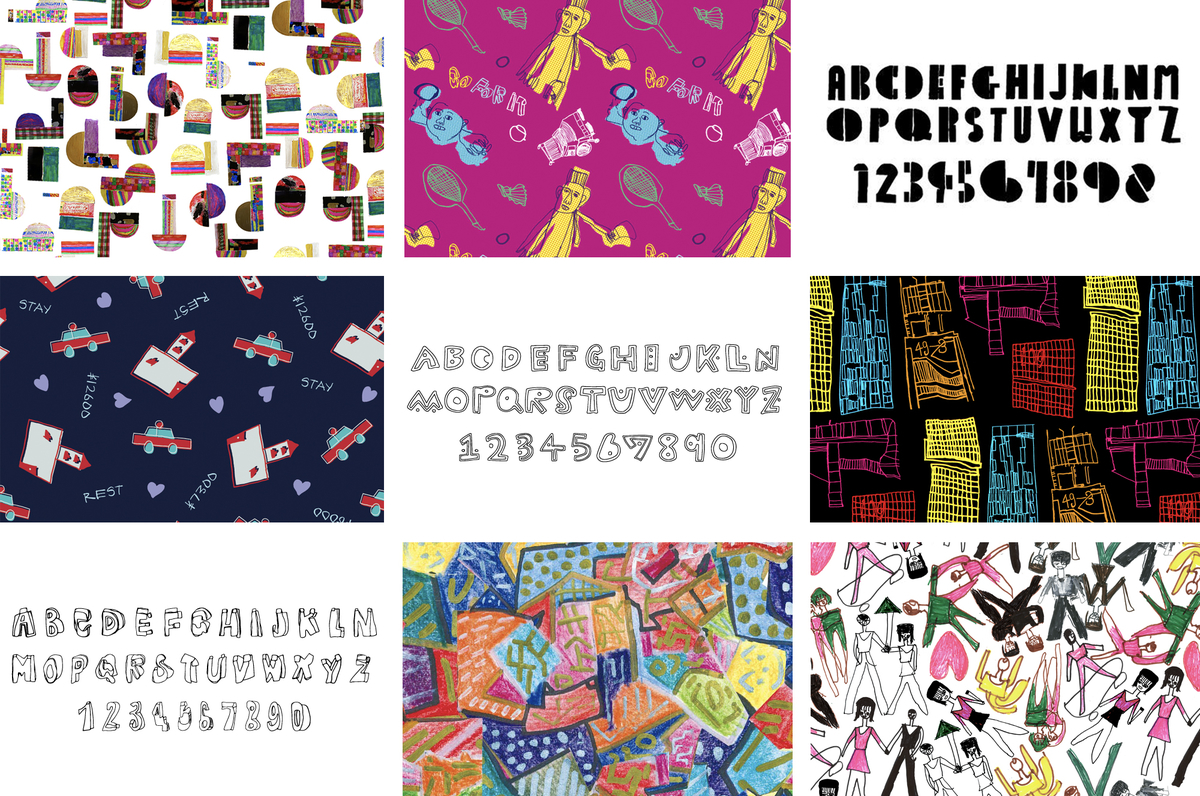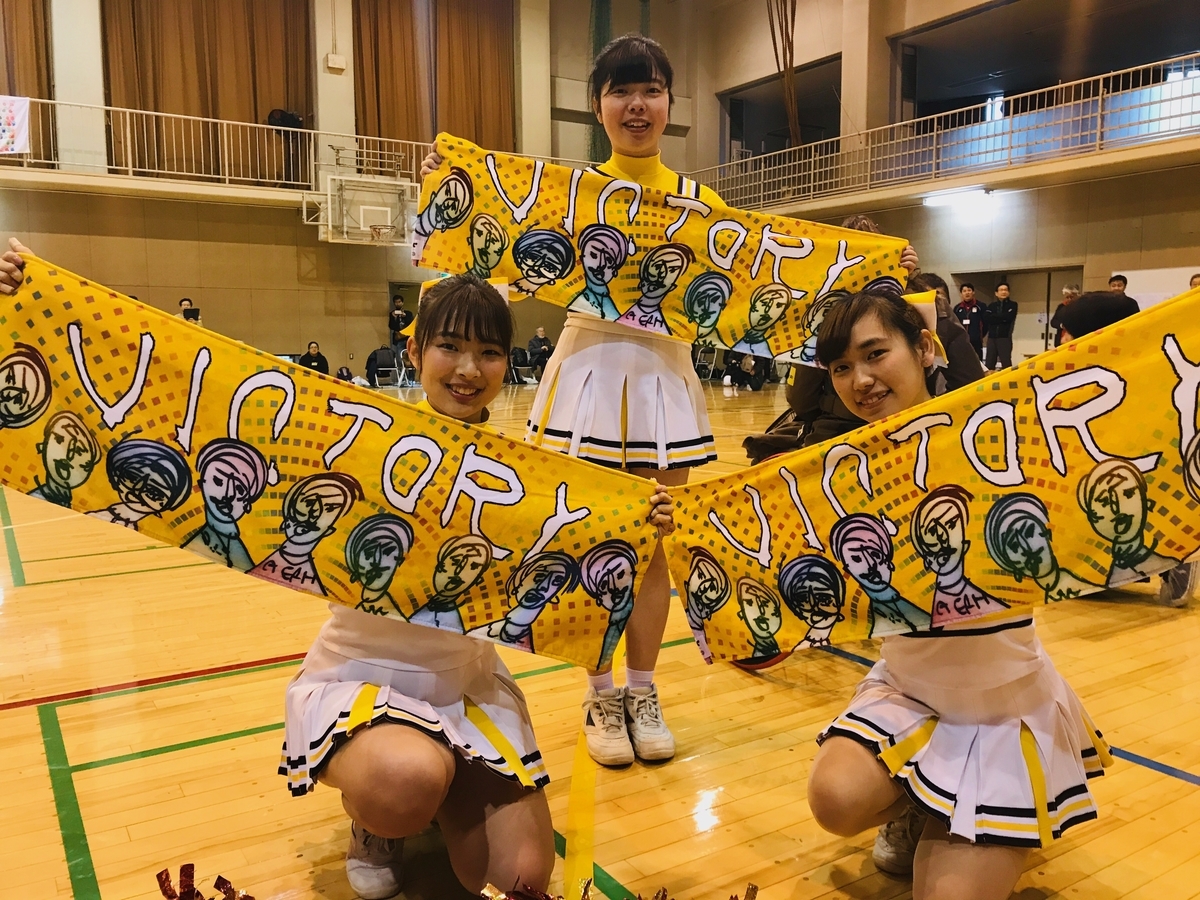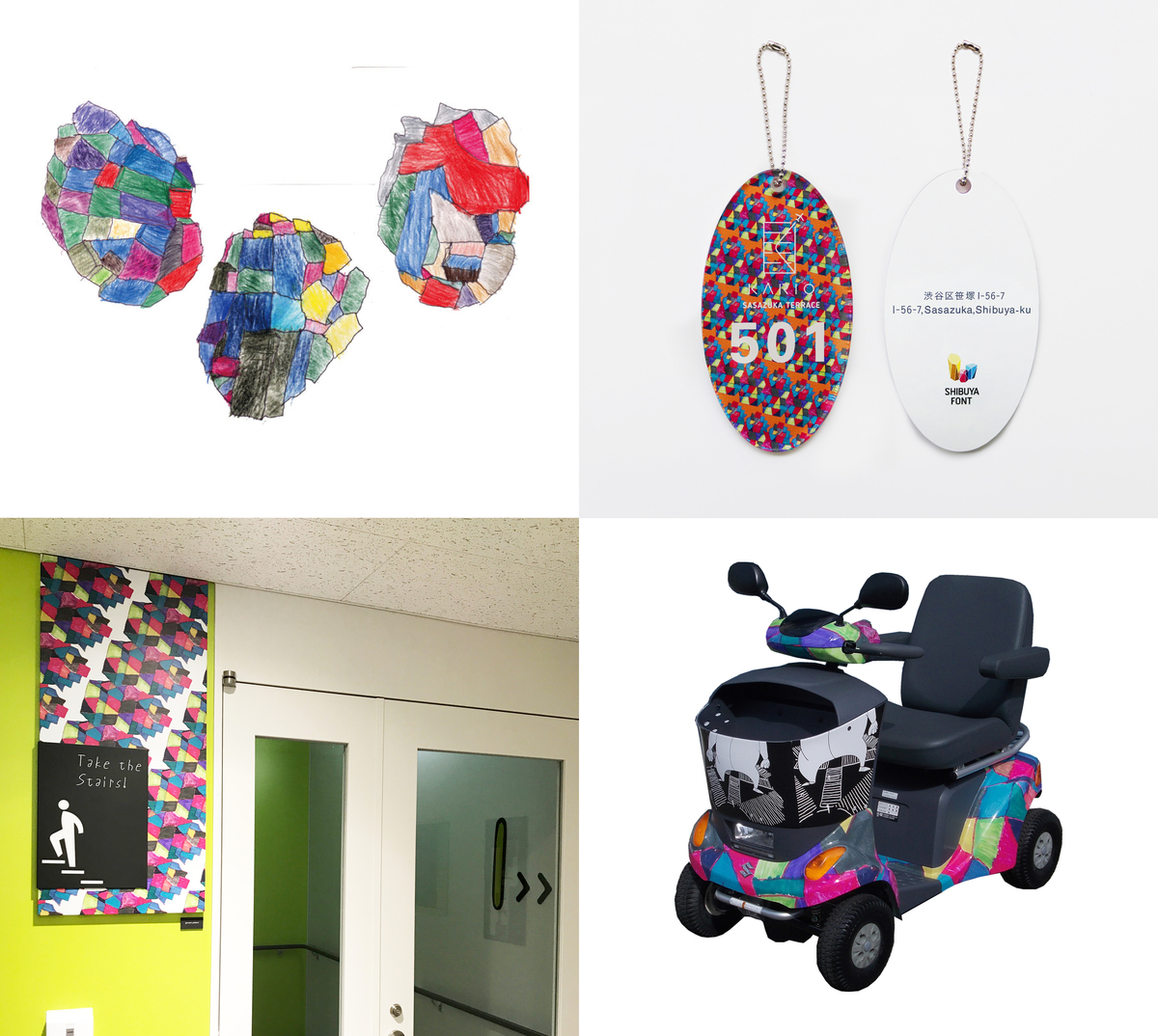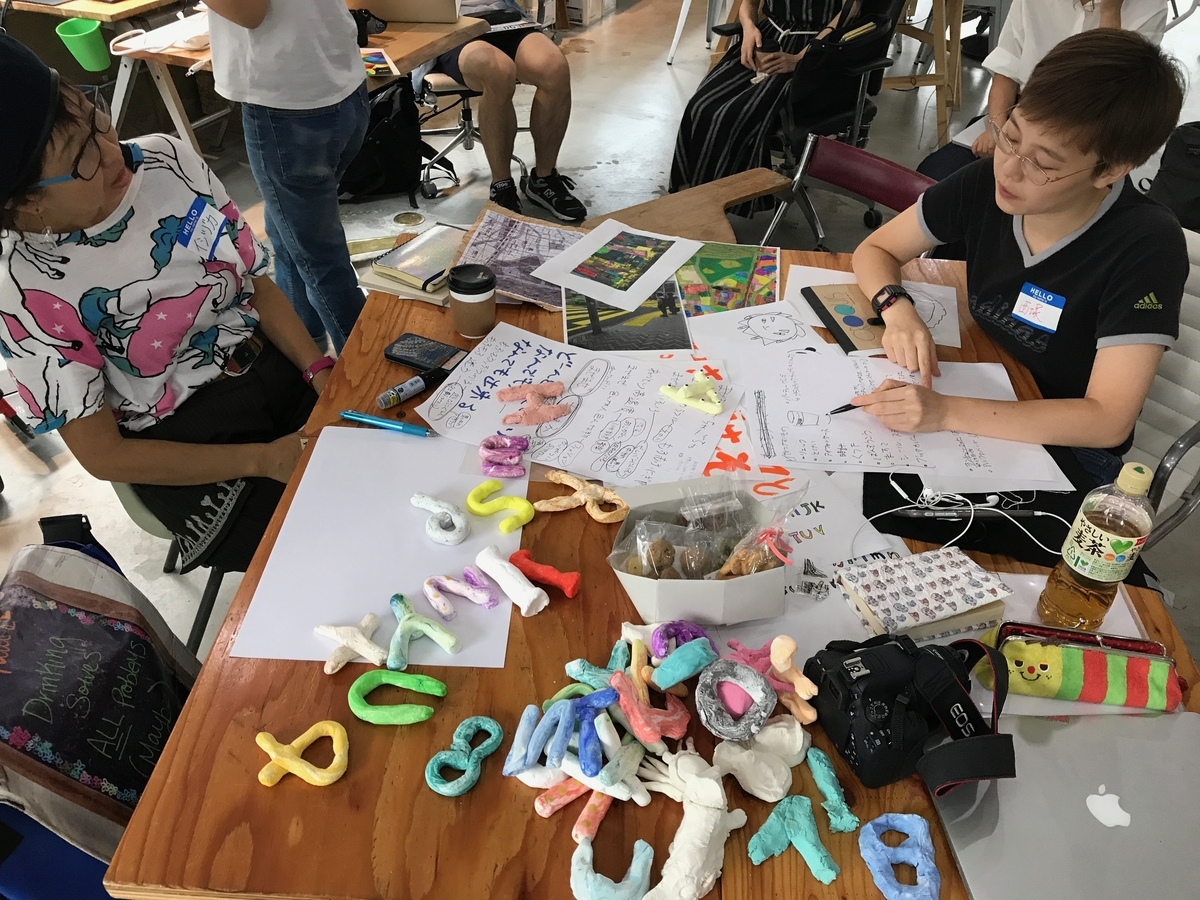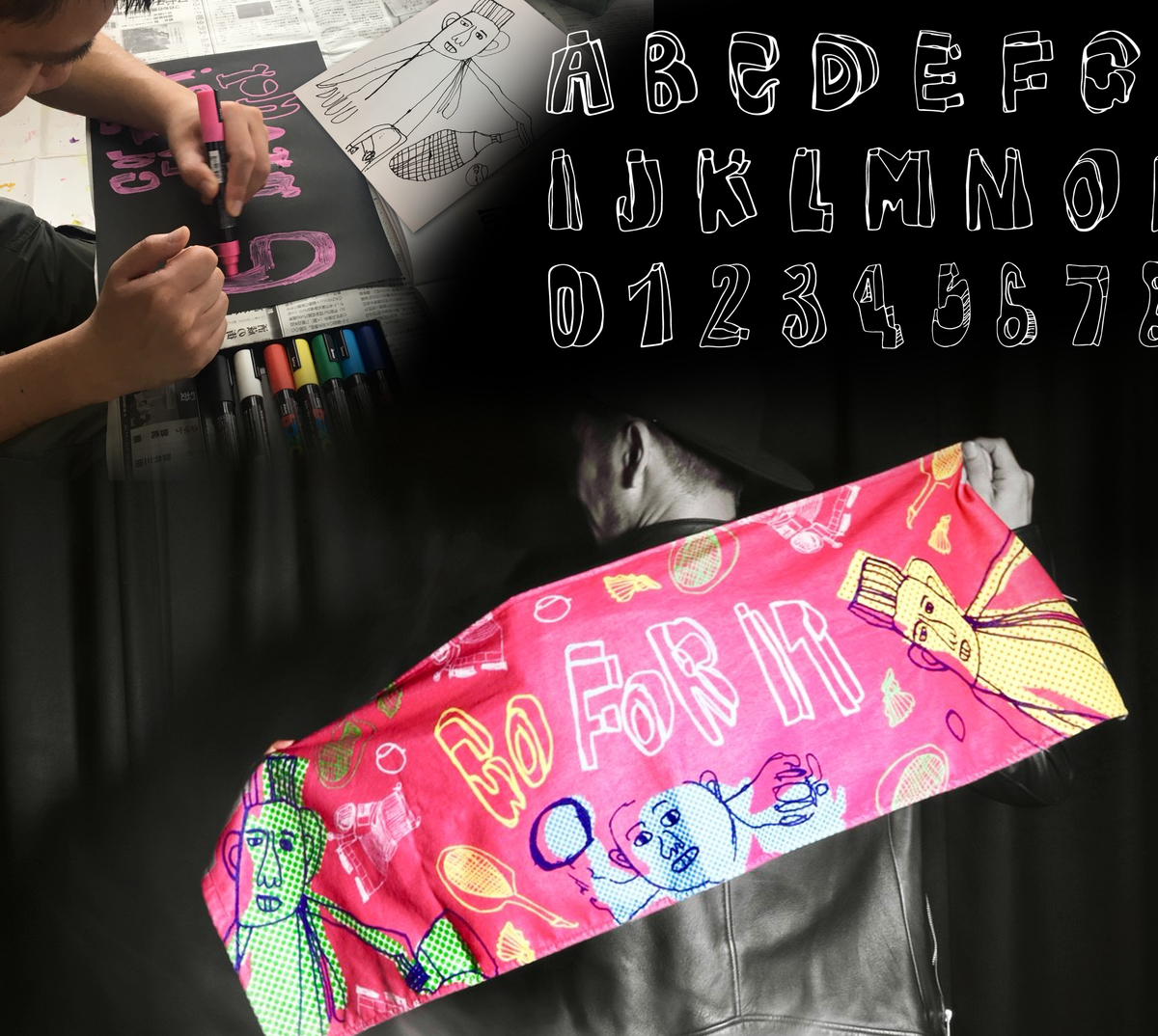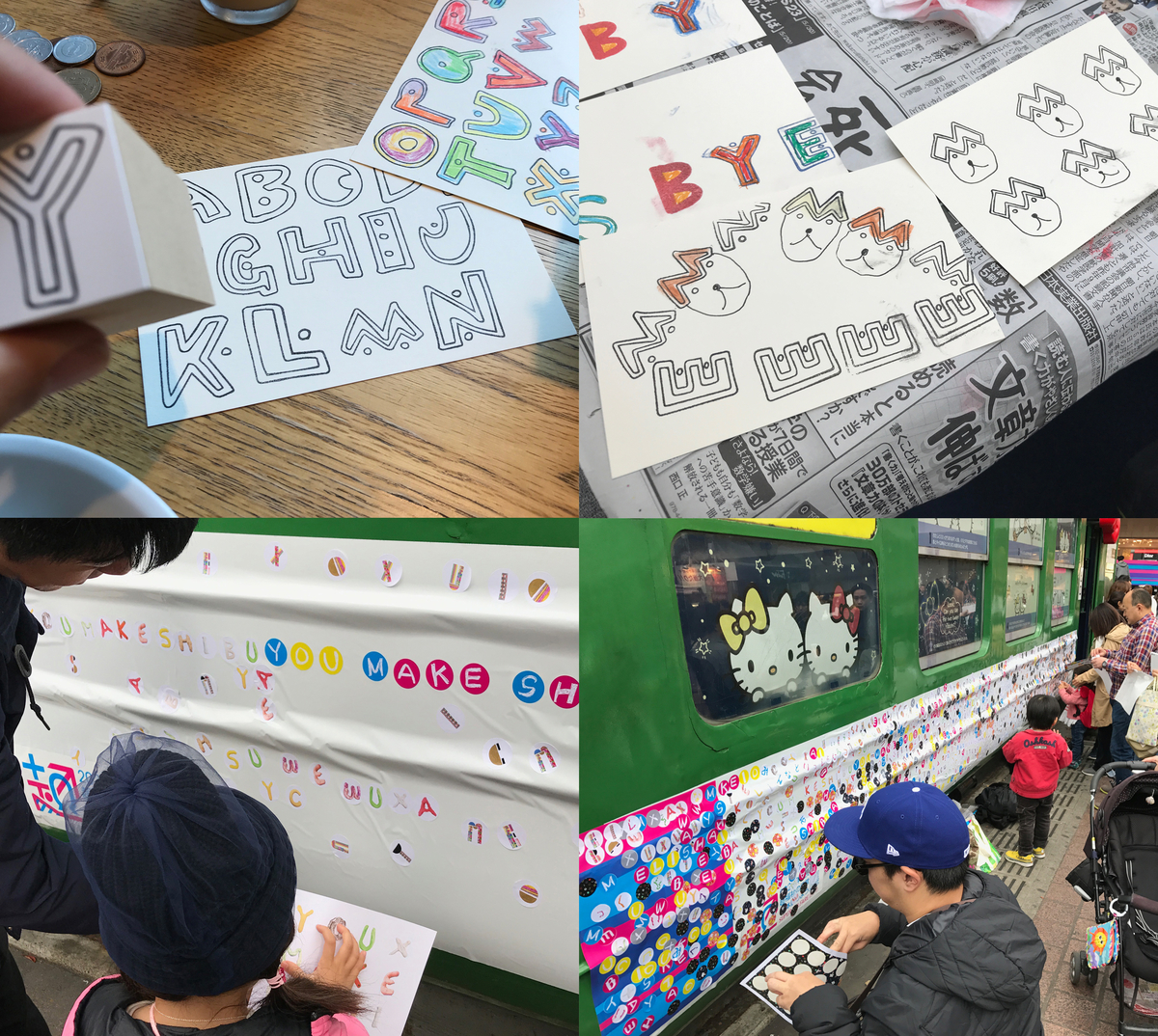
シブヤフォント
商標登録 第5991327号。渋谷区内の障がいのある人が描いた文字や絵から、専門学校桑沢デザイン研究所の学生がフォントやパターンデータを制作(2019年10月時点で100種以上)し、それらを渋谷区公認のパブリックデータ「シブヤフォント」とし、誰でも利用できるよう公式サイトで公開している。
また、シブヤフォントを採用した商品も販売し、売上の一部を渋谷区内の障害者支援施設に還元。渋谷区では新庁舎やLINE CUBE SHIBUYA(渋谷公会堂)の内装に採用、また同区職員の名刺、パソコンにインストールするなど導入を進めている。
“共に制作する””気軽に使える””商品に採用する”という誰でも参加できるデータの特性を活かして、渋谷区のダイバーシティ、インクルージョンの理念を広げている。
「シブヤフォント」が2019年度グッドデザイン賞を受賞
フクフクプラス、渋谷区、専門学校桑沢デザイン研究所、渋谷区内の障害者支援施設と共同する「シブヤフォント」が2019年度グッドデザイン賞を受賞した。
また、東急レクリエーション、渋谷サービス公社と連携し、シブヤフォントを採用した新商品200種以上を11月1日に開業する「渋谷スクランブルスクエア」の展望施設「渋谷スカイ」のショップにて販売される。
「シブヤフォント」グッドデザイン受賞について
受賞対象名:障がい者理解に向けたソーシャルアクション [障がいのある人が描く文字や絵柄をフォント・パターン化したパブリックデータ「シブヤフォント」]
受賞対象:渋谷区、専門学校桑沢デザイン研究所、株式会社フクフクプラス
事業主体:渋谷区
プロデューサー:渋谷区長 長谷部健
ディレクター:専門学校桑沢デザイン研究所/株式会社フクフクプラス 磯村歩、グラフィックデザイナー・アートディレクター ライラ・カセム
デザイナー:専門学校桑沢デザイン研究所、ストライドクラブ、のぞみ作業所、はぁとぴあ原宿、工房ぱれっと、ふれんど、アトリエ福花、むつみ工房、ワークささはた、ワークセンターひかわ、株式会社渋谷サービス公社
〇審査員の評価(出典元:グッドデザイン賞 公式サイト)
フォントへと落とし込むまでに相当の苦労があったと思う。デザインを学ぶ学生達が関係を持ち、製作するまでの教育的な観点や後の展開方法に至るまでデザイン的視点の眼差しが形となっていると思う。併走された教職員の方々と関係者の協働はクリエイティブのアウトプットに表現されている。ここから、渋谷区全域そして他地域へと方法論が共振していくように持続する形態となるよう願っている。
シブヤフォント商品の販売について
11月1日に開業する「渋谷スクランブルスクエア」の展望施設「渋谷スカイ」のショップでは、シブヤフォントの新商品200点以上を販売される。シブヤフォントのグラフィックの中から、渋谷の名所にちなんでスクランブル交差点に仁王立ちする巨人やホテル街を描いた作品など、ユニークなお土産として楽しんでもらえるものがラインナップ。売り上げの一部は障害者支援施設に還元される。